Auszeichnen
In der Typografie ist der Begriff »Auszeichnen« mehrdeutig. Er bezeichnet zum einen das Auszeichnen eines Typoskripts als Vorlage für die Satzherstellung, zum anderen die Schriftauszeichnung zur selektiven Schriftmischung oder Farbauszeichnung innerhalb eines geschlossenen Schriftsatzes.
1. Auszeichnen eines Manuskripts bzw. Typoskripts
In der Typografie versteht man unter »Auszeichnen« die makro- und mikrotypografischen Satzangaben für ein Manuskript (handschriftlicher Beitrag eines:einer Autor:in, der als Vorlage zur Vervielfältigung dient) bzw. für ein Typoskript (maschinell verfasster Text, der als Vorlage zur Vervielfältigung dient), die einem Schriftsetzer:in vorgibt, mit welchen charakterisierenden Eigenschaften der Schriftsatz typografisch (um)gesetzt werden soll.
Dazu zählen beispielsweise Vorgaben für die Grundschrift, Auszeichnungsschrift, Schriftgrad, Zeilenabstand, Spationierung oder Konsultation. Weitere Parameter siehe Makrotypografie und Mikrotypografie. Für das händische Auszeichnen werden primär klassische Satzanweisungs- und Korrekturzeichen verwendet.
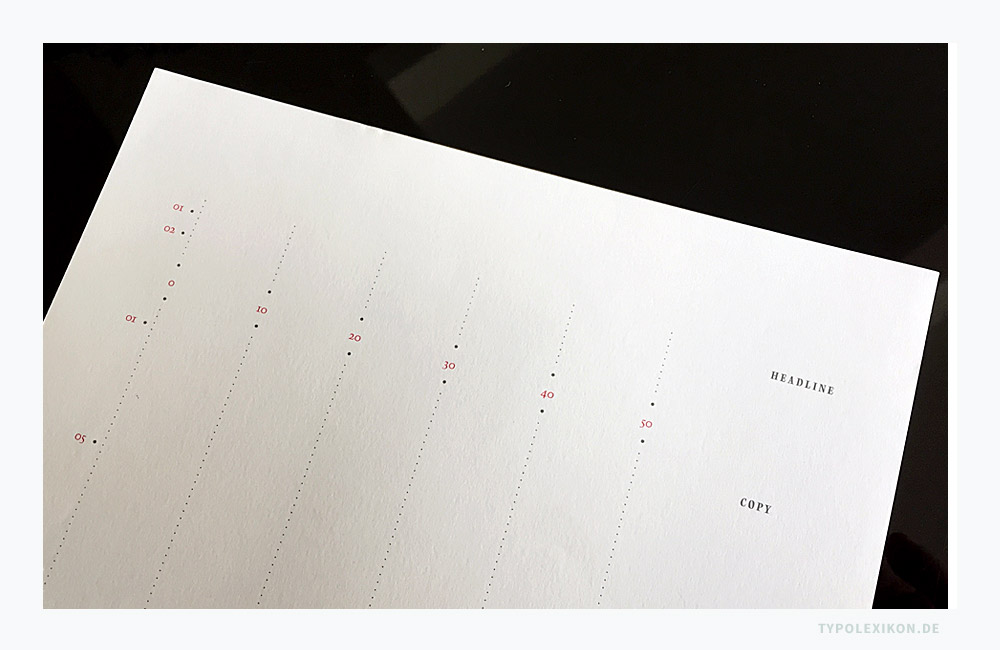
Bis zum Ende des optomechanischen Schriftsatzes (Fotosatz) gehörte das Auszeichnen von Manuskripten und Typoskripten zu den Routinen in der Zeitungs- und Buchtypografie sowie im Editorial-, Kommunikations- und Grafikdesign.
Mit Beginn der Elektronischen Textverarbeitung, insbesondere mit dem Gebrauch von Microsoft Word® (1983) sowie der Etablierung mittels professioneller Desktop Publishing Software (DTP), insbesondere durch Adobe PageMaker® (1985) und QuarkXpress® von Quark® (1987), geriet das händische Auszeichnen von Manuskripten oder Typoskripten aufgrund veränderter Arbeitsabläufe in seiner ursprünglichen Form sukzessive in Vergessenheit.
2. Auszeichnen im glatten und geschlossenen Schriftsatz
Das Auszeichnen im Sinne einer »Schriftauszeichnung« ist ein typografischer Terminus für eine selektive Schriftmischung oder Farbauszeichnung im glatten Satz bzw. innerhalb eines geschlossenen Schriftsatzes; es bezeichnet die Auszeichnung der Grundschrift innerhalb eines fortlaufenden Textes mit einer anderen Schriftart, Schriftstilvariante oder Schriftfarbe. Abk. »Auszeichnung«.